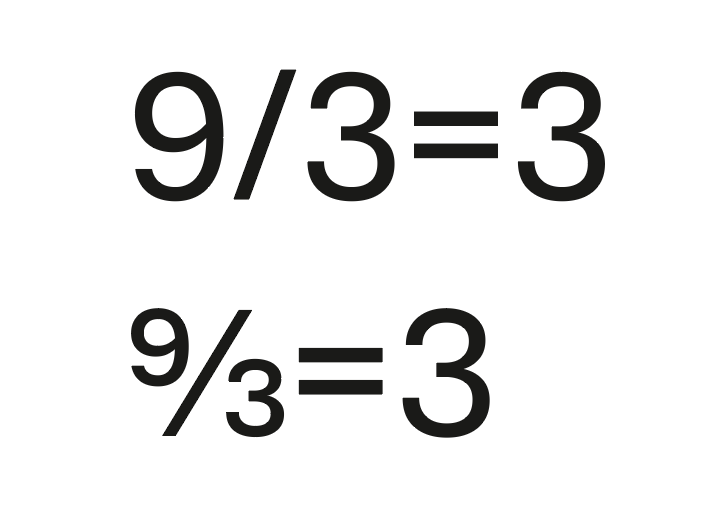
Im Formelsatz: Schrägstrich "/" oder Strichdoppelpunkt "÷" für "geteilt"?
Der Bruchstrich U+2044 ermöglich es, beliebige Brüche mit verkleinerten Zählern und Nennern zu schreiben.
Dafür muss die Schrift aber auch mit den kleinen Zahlen entsprechend ausgestattet sein. Gegebenenfalls wird die Darstellung durch eine Opentype-Funktion unterstützt.
Viele Schriften enthalten standardmäßig ¼, ⅓ und ⅔ als eigene Glyphen.
Im Textsatz geht es aber darum, die mathematische Operation mit normalen Zeichen möglichst einfach darzustellen. Das geht dann sogar mit einer Schreibmaschine. Dafür ist der einfache Schrägstrich vollkommen ausreichend.